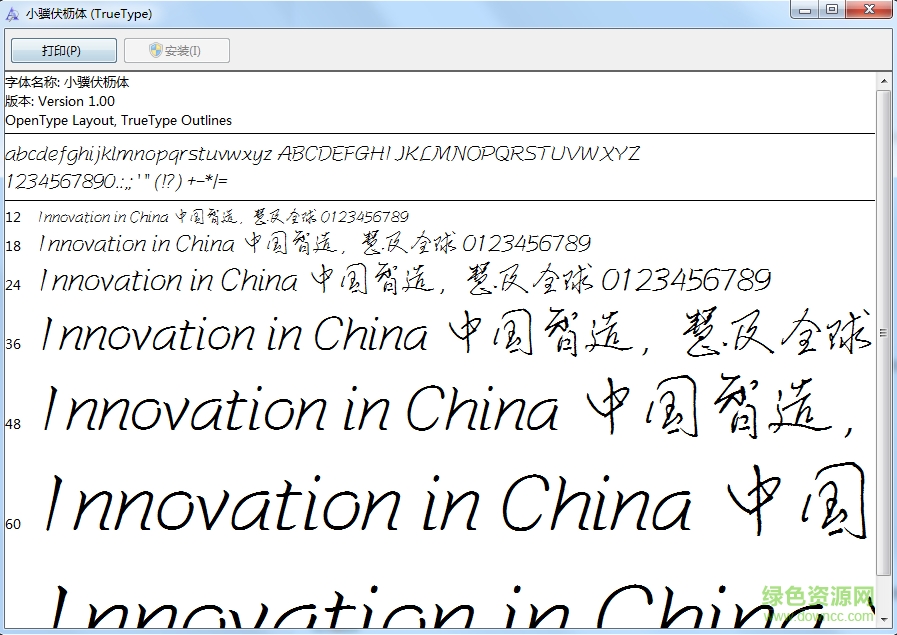
小驥伏櫪體是一款以草書為模板的方正字體,盡顯簡(jiǎn)約飄逸之美,適合文章排版、海報(bào)設(shè)計(jì)、廣告創(chuàng)意等多種行業(yè),綠色資源網(wǎng)為大家?guī)砻赓M(fèi)版,歡迎體驗(yàn)!
小驥伏櫪體是方正旗下有個(gè)性有古風(fēng)草書韻味的手寫體,娟秀簡(jiǎn)介,不拖泥帶水,給人直觀而清晰的視覺呈現(xiàn)。